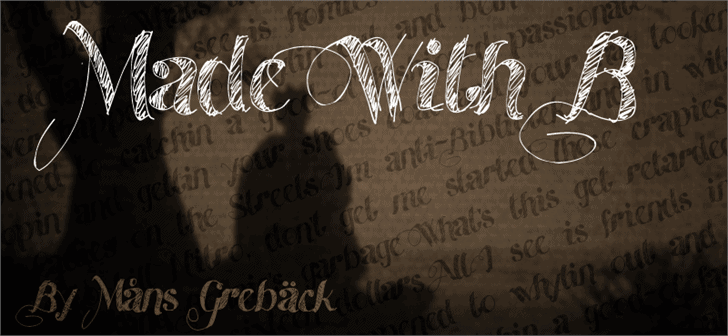
A fonte “Made With B” é uma escolha perfeita para quem busca estilo elegante e fluido no seu design. Criada por Hamilton, essa fonte Script se destaca com linhas suaves e letras levemente curvadas que permitem um texto fluente e vibrante. Perfeita para aplicações como websites pessoais ou criação de branding em projetos comerciais, a “Made With B” oferece uma experiência visual sofisticada sem sair da sua tela. Para usuários que estão prontos para explorar essa fonte, nós do Made With B apresentamos as condições específicas para um licenciamento comercial. Para adquiri-los, dê uma olhada em nossa página oficial: http://www.mansgreback.com/made-with-b. Com a “Made With B”, seus designs ganham vida com esse estilo único de letra fluida e elegante, tornando-a uma ótima opção para designers gráficos que desejam dar um toque especial em suas criações.